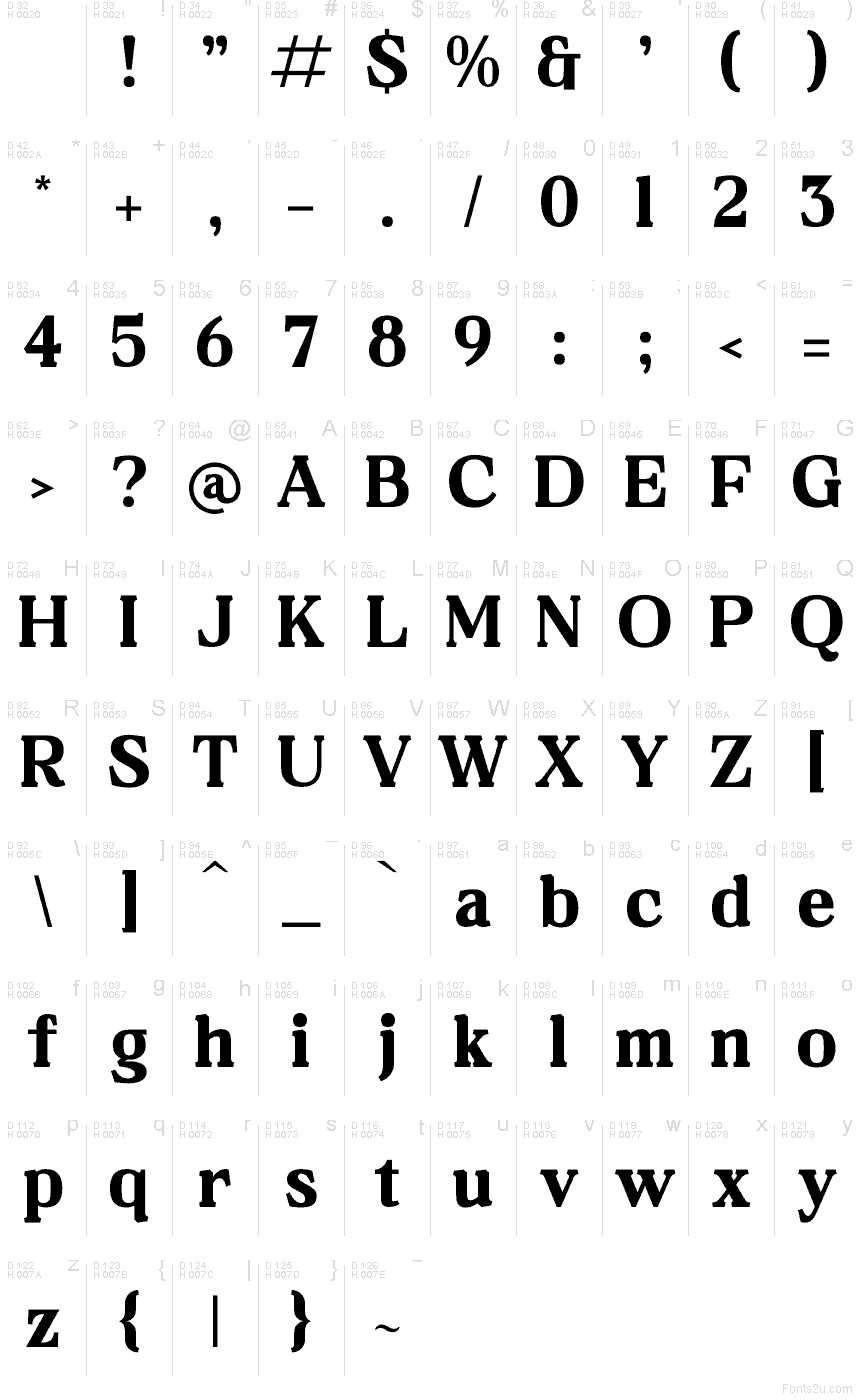
Neraphic
Neraphic, bezplatné písmo od Storytype Studio, kombinuje široké zaoblené tvary s ostrými, rozšírenými pätkami, ktoré dodávajú písmenám vyrezávanú, až divadelnú siluetu. Tento kontrast medzi jemnými krivkami a špicatými detailmi spôsobuje, že dizajn pôsobí premyslene a vznešene, nie len tradične.
Skvele vynikne na knižných obálkach, obaloch butikových značiek, v brandingu reštaurácií, na plagátoch a v redakčných nadpisoch, kde pätkové písmo potrebuje viac charakteru než bežný klasický štýl. Zaoblená hmota dodáva krátkym slovám silnú prítomnosť, zatiaľ čo zúžené konce a ostré rezy prinášajú dostatok dramatičnosti pre logá a hlavné tituly.